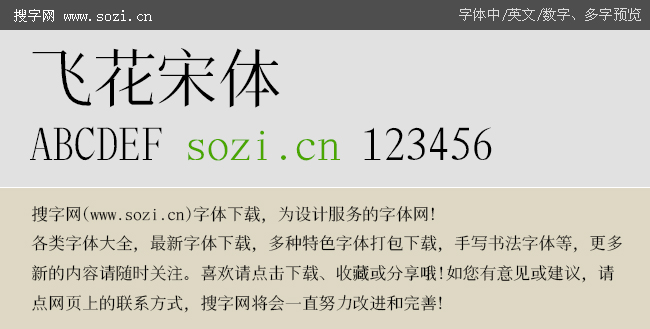
飛花宋體
搜字網(wǎng)給大家提供一款飛花宋體中文字體下載,飛花宋體是一款宋體字體,字體簡(jiǎn)潔大方,方正耐看,視覺(jué)效果非常舒服。適用于書(shū)籍設(shè)計(jì)、海報(bào)設(shè)計(jì)、包裝設(shè)計(jì)、廣告設(shè)計(jì)等場(chǎng)景。